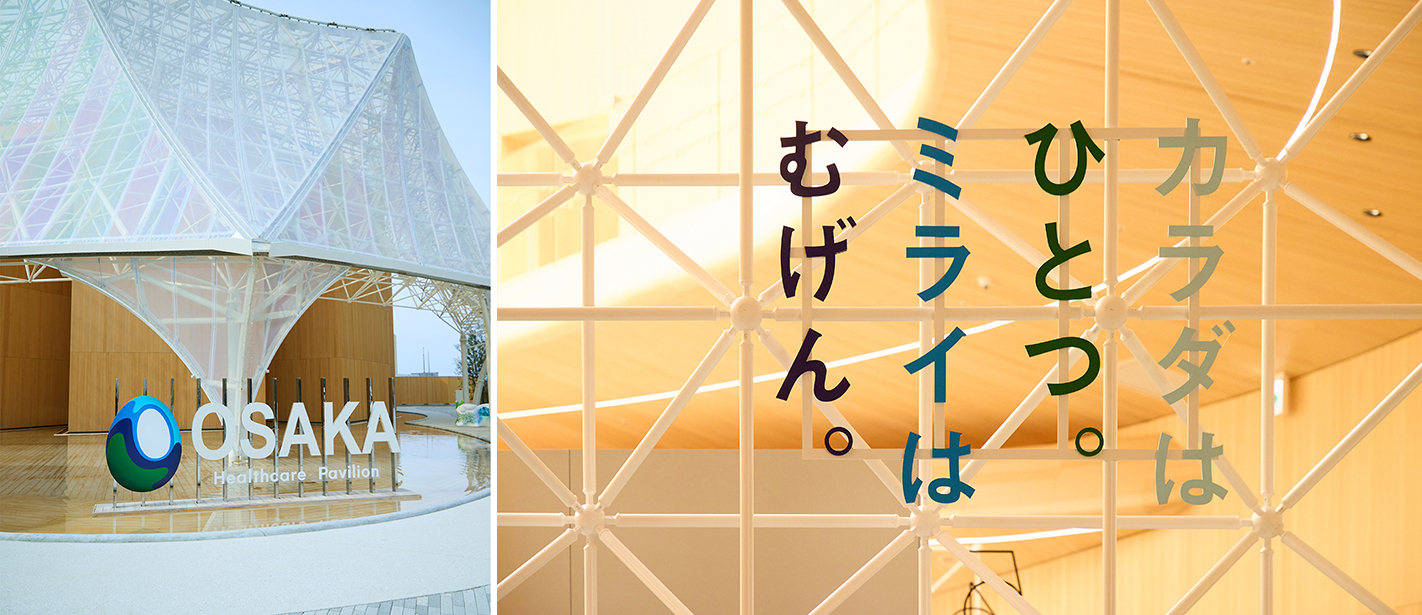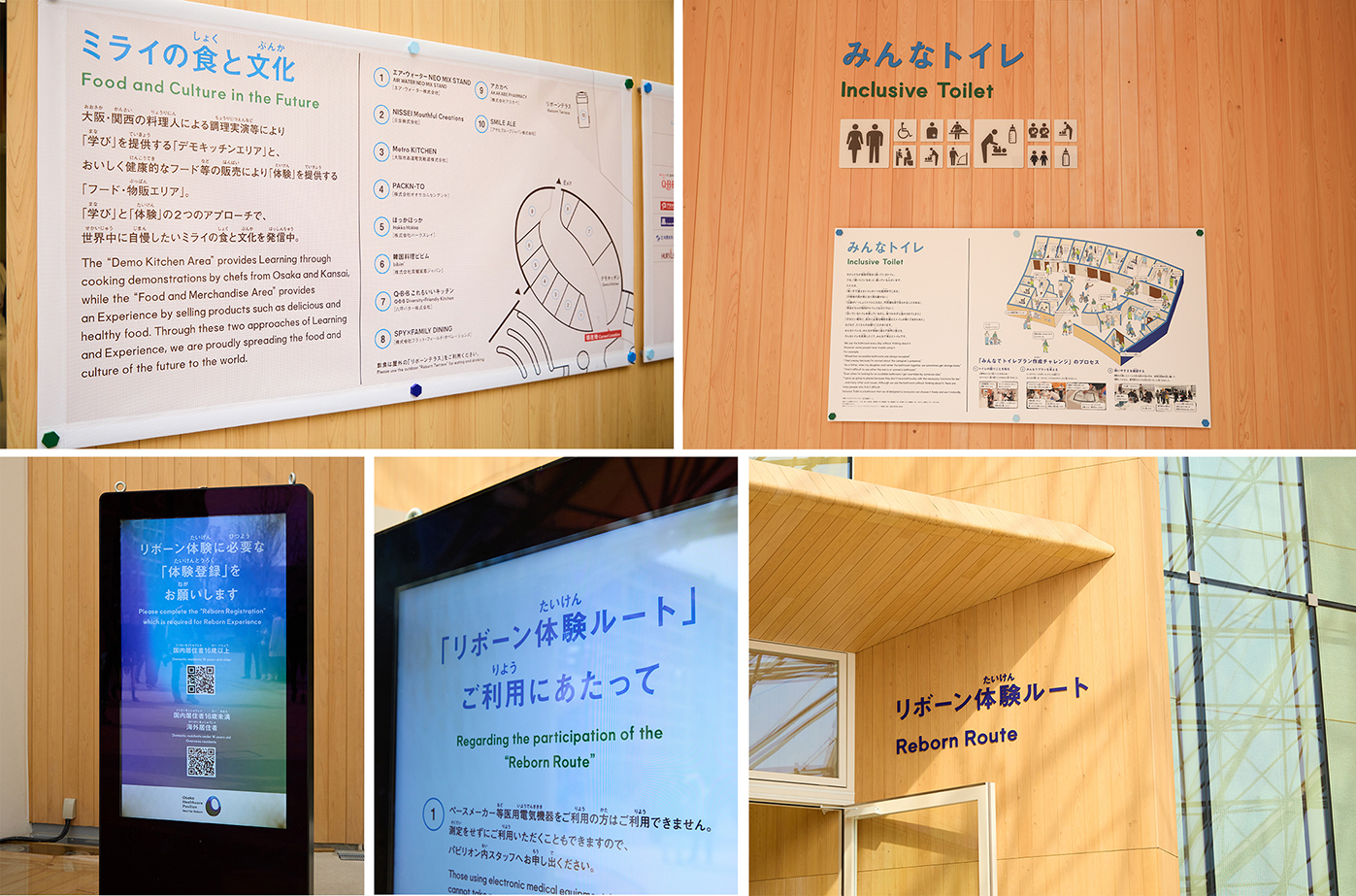
大阪・関西万博「大阪ヘルスケアパビリオン」来館者数100万人達成 「リボーン体験ルート」サインにはモリサワのフォント「見出ゴMB31」を採用
大阪府と大阪市などが出展する大阪ヘルスケアパビリオンは、REBORNをテーマに、25年後の自分(アバター)と一緒にミライのヘルスケアやミライの都市の体験を楽しむ「リボーン体験」などを展示しています。開幕以来、人気のパビリオンのひとつに数えられています。2025年5月28日(水)に予想を上回るペースで来館者数100万人を達成しました。これにともない、リボーンステージでは記念セレモニーが開催されました。
大阪ヘルスケアパビリオンでは、モリサワが提供する「見出ゴMB31」「太ゴB101」「ゴシックMB101 B」「UD新ゴ ハングル」などのフォントが、会場のサインやアプリケーション用組込みフォントに採用されています。見出ゴMB31は、伝統的で落ち着きのある見出し用ゴシック体で、ゴシック体のなかでは字面が小さめに設計されているため、大きなサイズで使うのに適した書体です。